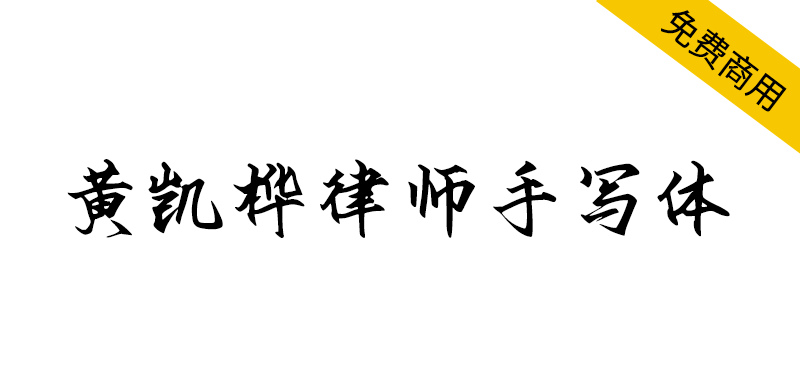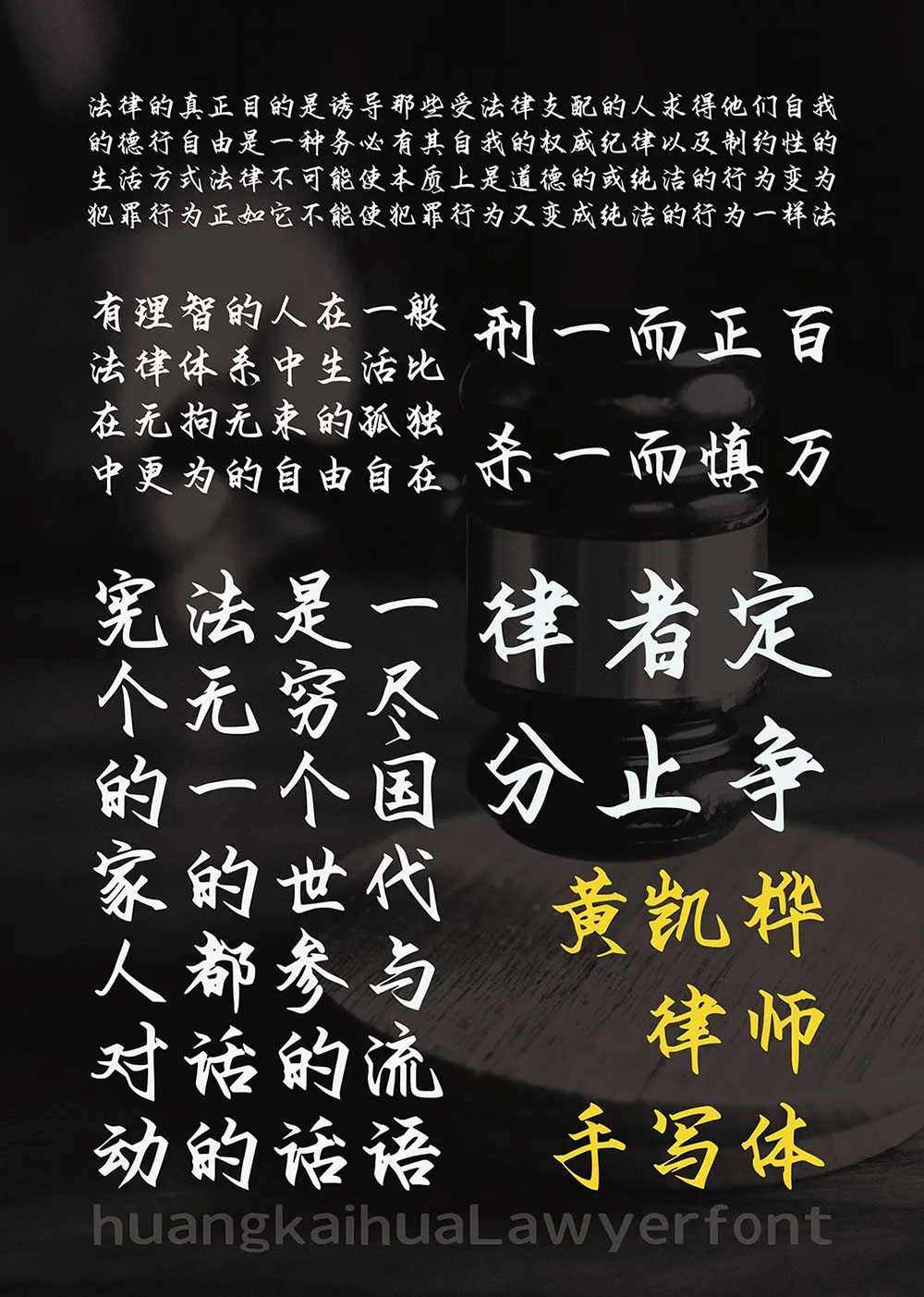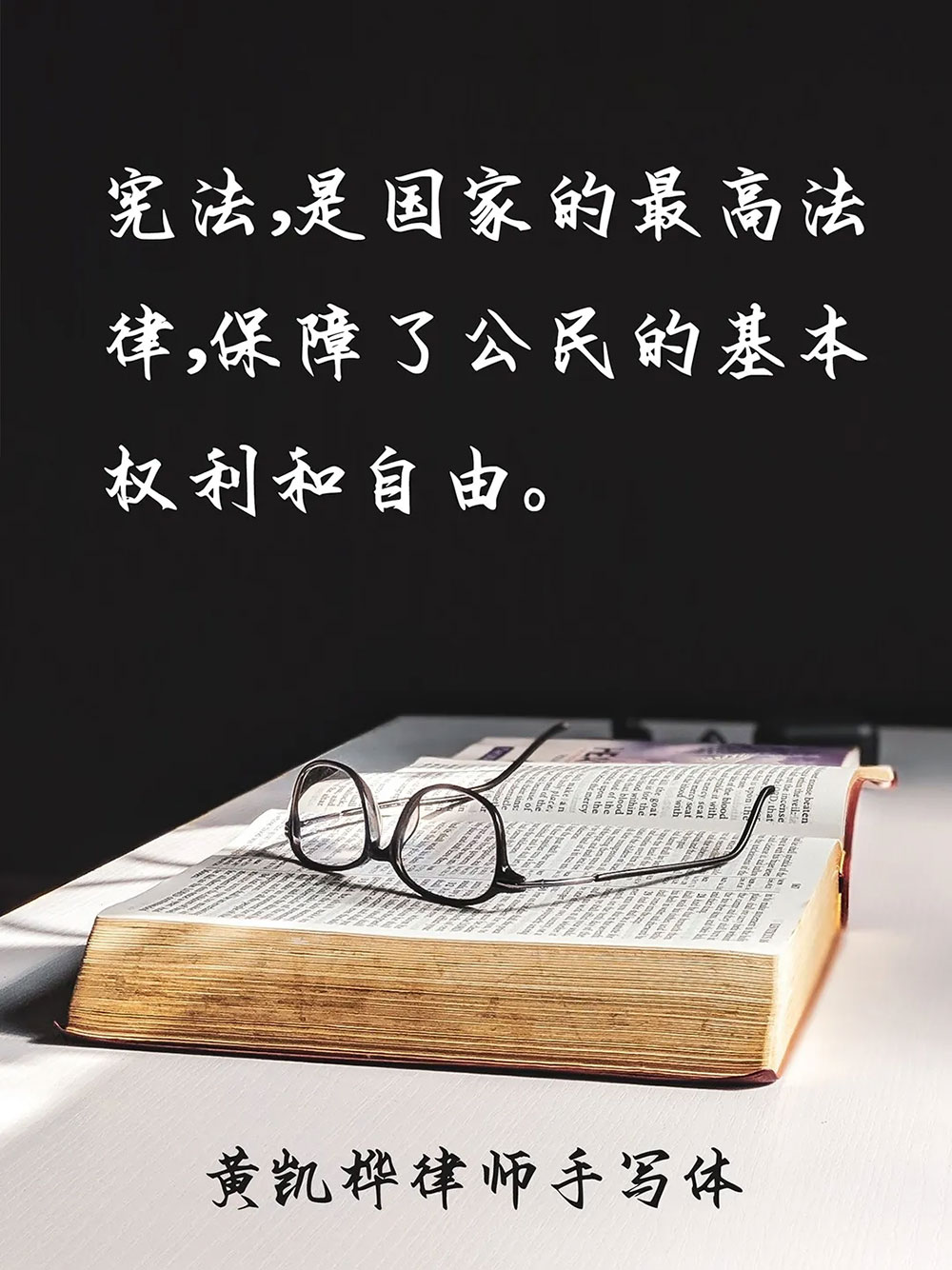
近年来,团队和本人在业务和生活中,接触到越来越多的企业因为字体侵权而蒙受损失的事情。
作为一名律师,对于字体使用事宜,一是尊重知识产权的维权。因为一套字体的产生,需要耗费大量的人力、时间和费用。但对很多企业来说,字体商业授权费用是一笔不小的费用;二是很多当事人不知道哪些字体可以免费商用哪些不能,以至于侵权或迷茫。
为此,机缘巧合之下,在咨询公司的帮助下,以本人美工笔手写字为基础,制作了这一套字体。基于对作者版权和律师行业的尊重,命名为“黄凯桦律师手写体”。
也许,这是国内律师行业第一套免费可商用中文字体。
黄凯桦律师手写体简介:黄凯桦律师手写体(作品登记证书登记号:陕作登字-2024-F-00013739),是一套根据简体中文汉字编码国家标准(GB2312编码)设计的字体,并在此基础上一共设计了6769个简体汉字,为一款原创字体,具有其独特的字形风格,适用于广告、书籍、海报等多个场合。
希望通过这套字体,让更多的企业、组织和设计师设以及其他相关人员,了解到字体的合法使用,也可以多一套可以免费商用的字体,少一些侵权风险。